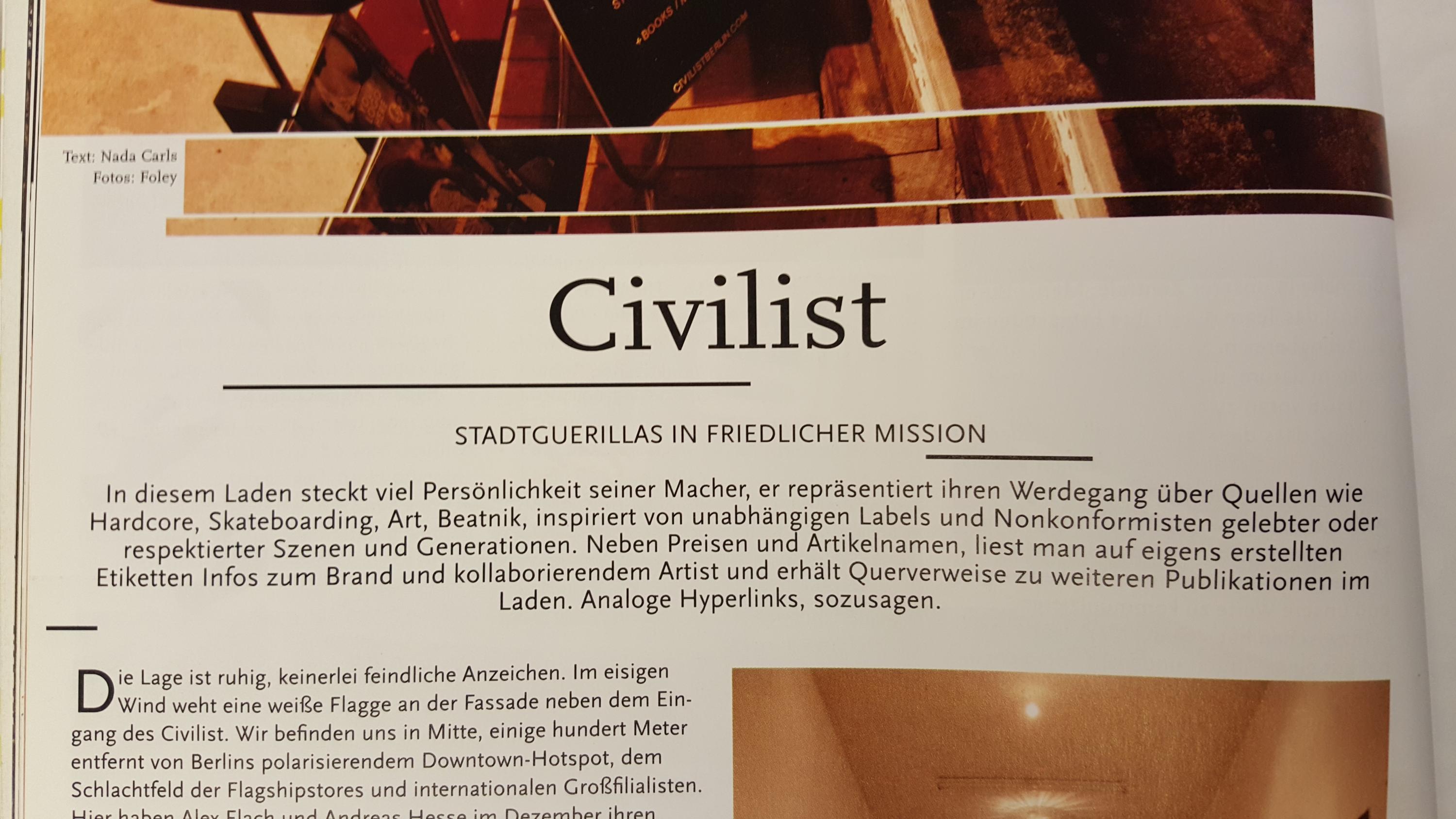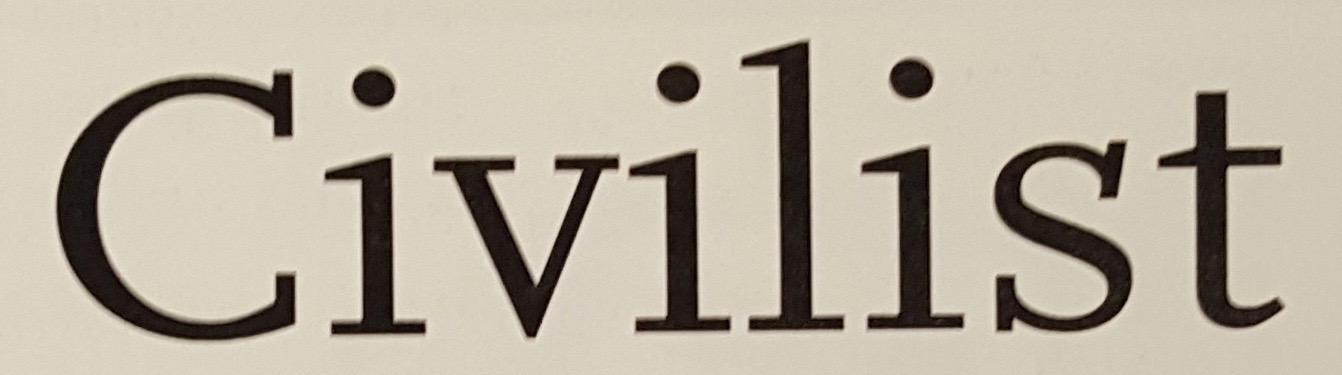
Zwei Magazin-Schriften dringend gesucht
ich bin ein Neuling was Typografie anbelangt und muss für die Uni ein (Grundraster für ein) Magazin nachbauen. Dazu soll ich nun möglichst die gleichen Schriften benutzen oder welche, die ihnen sehr nah kommen. Die Officina Sans schien für mich dem Fließtext anfangs am meisten zu ähneln, nur das W hatte leider nicht gepasst. Momentan tendiere ich jetzt aber stark zur Scala Sans Regular für die Grotesk und die Scala Regular für die Serifenschrift.
Was haltet ihr davon?
Wenn du bei issuu das pdf herunterlädst und nachschaust, bekommst du die Schriften angezeigt: